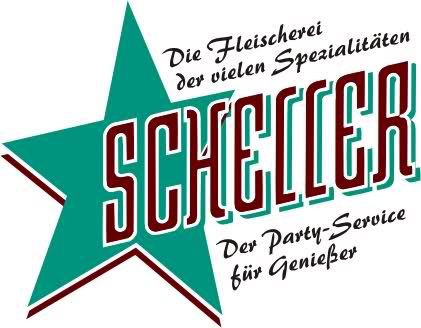
Wer kennt diesen von von 1959 oder so????
Ich suche den Font von Scheller in dem Logo. Kann mir da jemand helfen?
Ja, danke, ich denke auch, dass es handgeschnitzt ist.. lach... die brush interessiert hierbei nicxht...